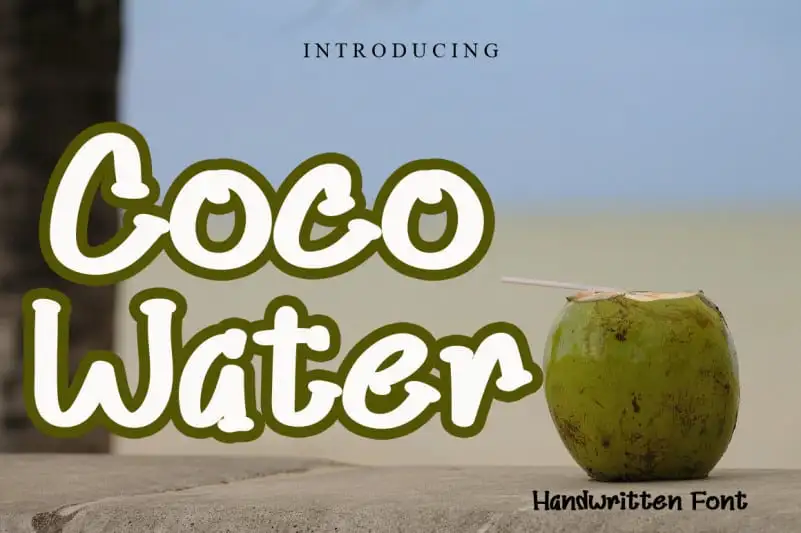
A Coco Water Display Font é uma seleção incrivelmente peculiar e encantadora para criar designs exuberantes. Seja você que trabalha com ilustrações infantis, jogos infantis ou mesmo qualquer criação onde um toque alegre seja desejado, esta fonte trará uma experiência memorável ao seu projeto. Com seu tom docil e suave, ela se encaixa perfeitamente para aqueles momentos em que você quer que sua obra prima seja ainda mais encantadora. Seja o criador de cartazes de jogos ou a designer de jogos interativos, a Coco Water Display Font é uma escolha imperdível para dar um toque único e irresistivelmente alegre às suas criações.